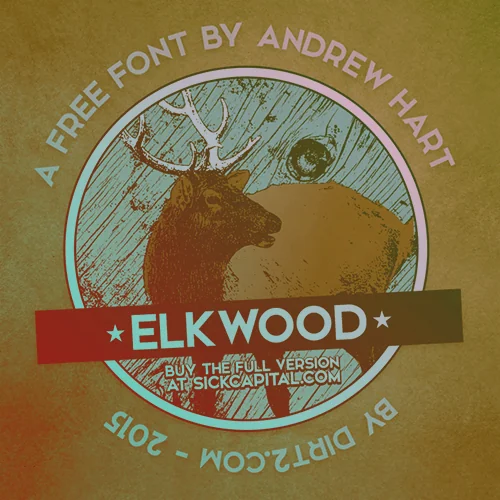
9 tipografías frescas para diseñadores
Aquí tienes tipografías frescas para diseñadores gráficos. Un regalito para que empieces la semana con buen pie :). Es una recopilación de fuentes nuevas, que harán que tus diseños tengan vida y personalidad. Su descarga es gratis.
Como siempre he intentado que haya un poco de todo, para titulares, tipografías finas, simulando escritura a mano… escoge las que más te gusten y guardalas en tu colección de fuentes.
Elkwood
Fuente ideal para titulares, es gruesa, se lee bien y crea impacto.
Refuge fuente gratis
Tpografía tipo vintage. Ideal para proyectos donde se requiera una fuente de tipo escrita a mano.
Panton
Es una tipografía que tiene gran cantidad de grosores. En este caso, tienes de forma gratuita 4 grosores distintos de la misma fuente.
Kino 40
Es una tipografía que la puedes utilizar gratis tanto para proyectos personales como comerciales. Es de estilo de escritura a mano.
Sunn
Otra fuente del tipo de las que simulan la escritura a mano. La puedes utilizar para cualquier tipo de proyecto, solo que para descargarla tienes que agregar al autor en alguna de tus redes sociales.
Cicero Serif
Es una fuente serif.
Pier
Es una fuente sans serif gratis. Tipografía de palo.